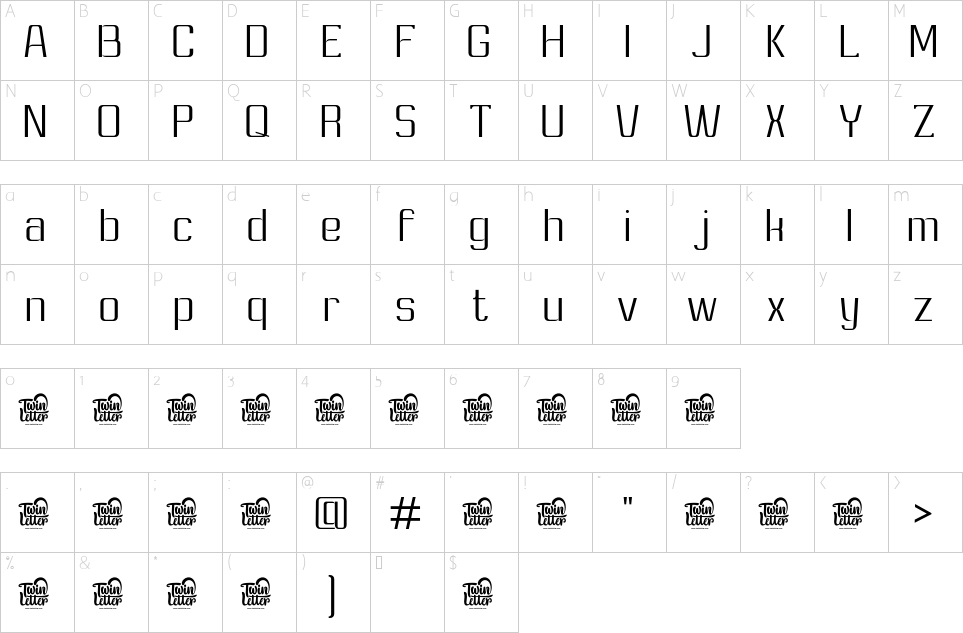
A Ashety Font é uma opção de fonte que combina elegância e modernidade, perfeitamente adaptada para estilos de design gráfico variados. Esta fonte foi criada por uma designer desconhecida e tem atraído muitos criativos ao redor do mundo. Com sua simplicidade e clareza, Ashety pode ser o elemento que dá um toque especial ao seu projeto. Se você está procurando por uma fonte moderna e fácil de ler para seus projetos de design, Ashety pode ser a fonte perfeita para você. Baixe agora e descubra por si mesmo o poder desta fonte.